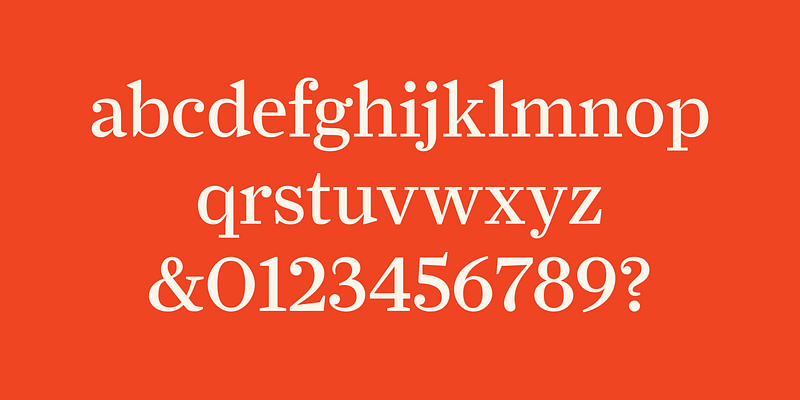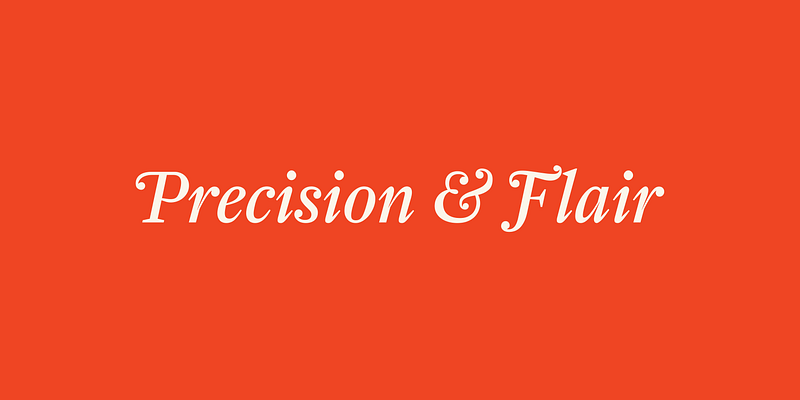
ドイツ生まれのパンチカッター、Johann Fleischman は、John Baskerville や Pierre Simon Fournier と同時代人で、ハールレムの Enschedé Foundry で働いていました。高度な工具と上質な鋼の品質に精通していた Fleischman は、当時の限界を超え、その「輝き」で世界的に有名なアクティブな書体をカットしました。Christian Schwartz は、Fleischman の活気に満ちた角張ったデザインに焦点を当て、それを Farnham シリーズ (テキスト、ディスプレイ、ヘッドライン、FB 2004、2016) のすべてのウエイトに取り入れました。
Christian Schwartz による新旧フォントメーカー
Orange Italic は、アートプロジェクト、デザインスタジオ、雑誌を経て、Christian Schwartz の初期のキャリアからのレガシー書体のライブラリとなっています。
2001 年に書体デザイナーの Christian Schwartz とデザインの博識家 Dino Sanchez によって最初に設立された Orange Italic は、アートプロジェクト、デザインスタジオ、雑誌を経てきました。2023 年現在、2009 年に Paul Barnes と Commercial Type を共同設立する以前の、Schwartz の初期のキャリアからのレガシー書体のライブラリとなっています。これらのほとんどは Font Bureau を通じてリリースされ、他の書体もようやく完成し、初めて一般リリースされています。影響力のある Amplitude や Farnham から無名の Fritz まで、これらのファミリーはすべて、以前はなかったファミリーの斜体や拡張された文字セットなど、現代の標準に合わせて更新されています。